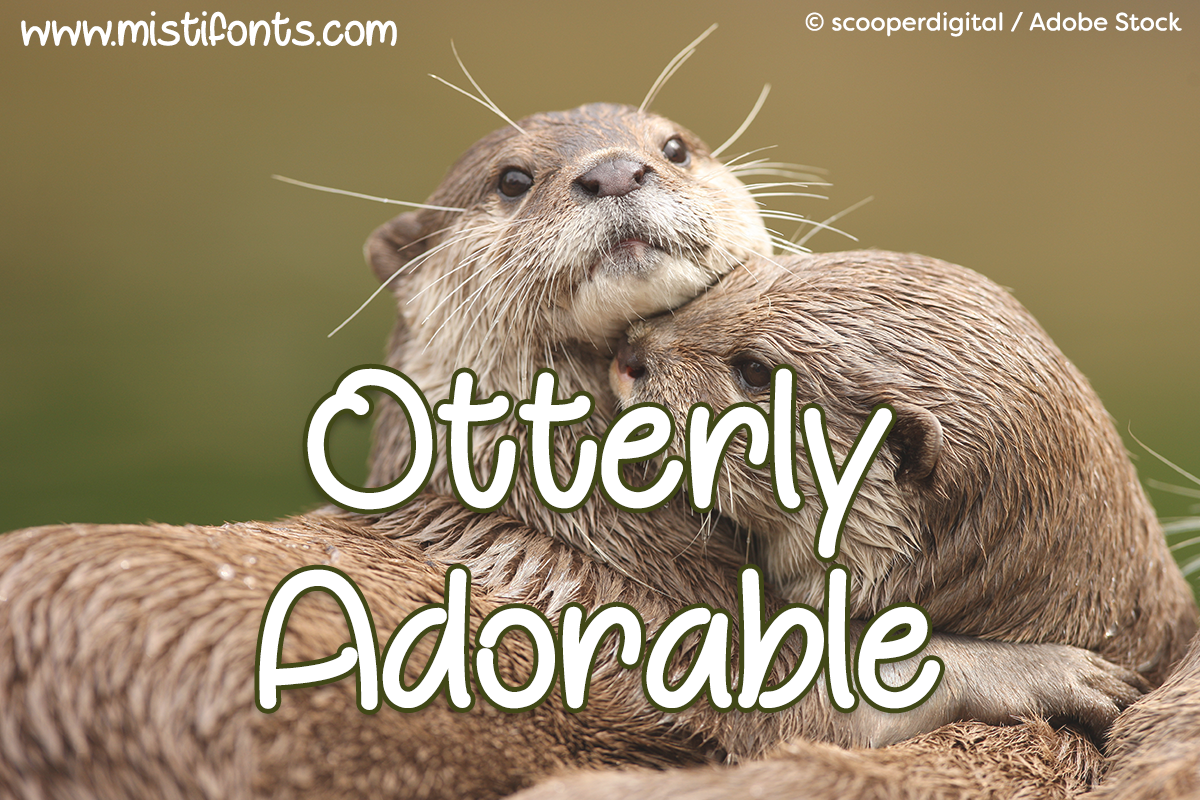
Otterly Adorable Script Font – Download Grátis
Esta fonte script ‘Otterly Adorable’ é perfeita para adicionar uma pitada de encanto ao seu design gráfico pessoal ou não-profit. Seu formato elegante e suave consegue transmitir um toque divertido com traços agradáveis, tornando-a ideal para nomes de empresas, rótulos de produto, logotipos e até mesmo para adicionar um charme especial às suas mensagens e cartões de aniversário. A designer Misti’s Fonts criou algo que pode ser usado sem qualquer custo adicional para fins pessoais ou não lucrativos, mas se você desejar usá-la em projetos comerciais, é importante comprar uma licença. A fonte ‘Otterly Adorable’ tem um apelo irresistível, tornando-a a escolha perfeita para aqueles que querem criar algo único e memorável.